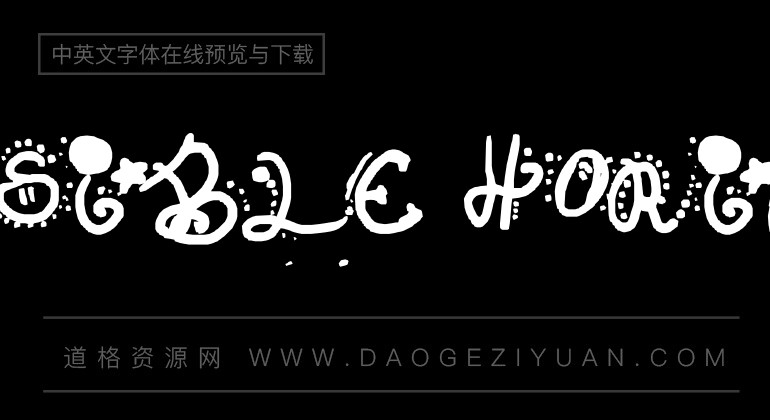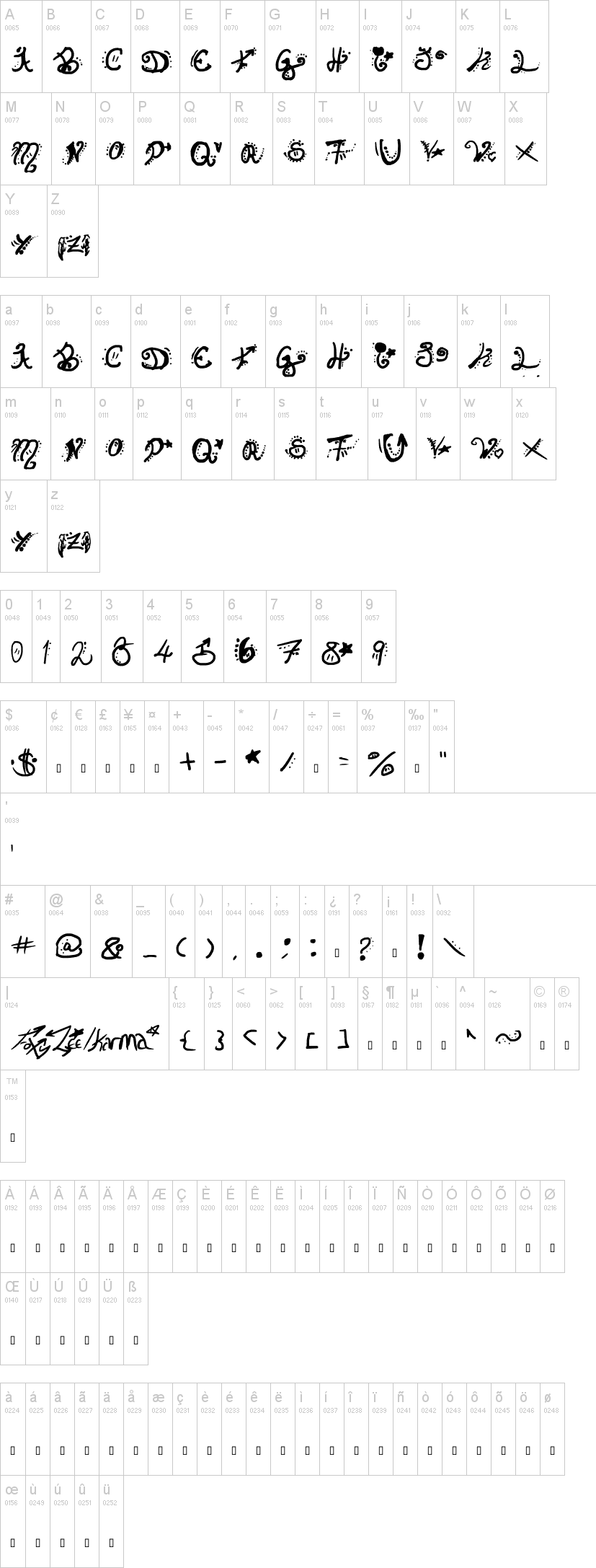
Invisible Horizons 是一款由MADType字体商店推出的一款定制字体,它拥有独特的抽象风格,具有抽象线条和精致的细节,可以为设计师提供更多的创意空间。它有着细腻的细节,可以使您的设计更加精致,而且它的字体结构也更加简洁,可以满足您的各种设计需求。它的字符结构也更加丰富,可以满足您的不同需求,而且还有一些特殊的字符,可以让您的设计更加有趣。内容介绍
Invisible Horizons是一款非常不错的手写艺术字体,具有很好的视觉感,适合于文化类的宣传设计、商业类品牌的广告和产品包装设计以及个性化文字排版等较多场景。